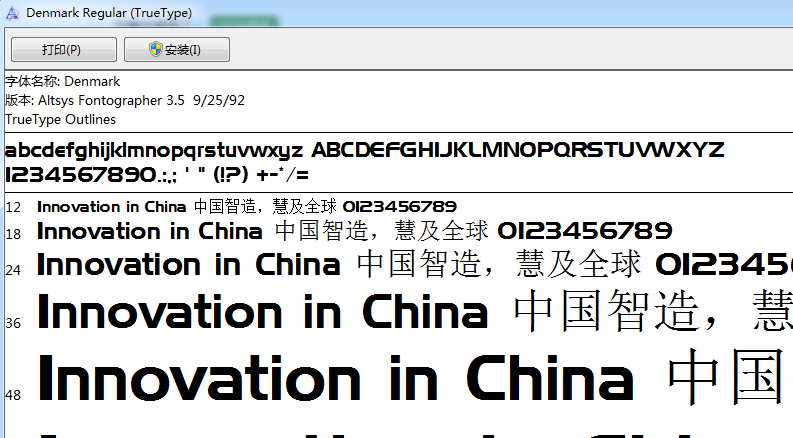
denmark
denmark免費版適用性非常強的電腦字體,這個字體一眼看上去就很美觀,視覺體驗很不錯,并且自帶加粗效果,在設(shè)計一些英文宣傳報、封面設(shè)計時都可以使用,能夠呈現(xiàn)出很顯眼的效果,其兼容性也很強,適用于多個不同的電腦系統(tǒng)。
denmark字體介紹:
denmark是非常漂亮的英文字體,深受廣大設(shè)計師喜愛,字體被廣泛用于廣告、海報、畫冊、包裝的設(shè)計及印刷中。
denmark字體
字體特色:
字體設(shè)計優(yōu)美、秀麗大方,書寫流暢,整體效果非常漂亮。
適合應(yīng)用于海報設(shè)計、書籍裝幀、畫冊封面、產(chǎn)品包裝設(shè)計等應(yīng)用。